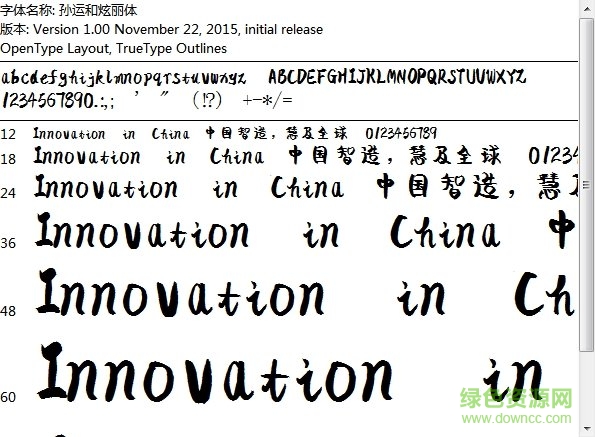
孫運(yùn)和炫麗體是一款字跡飄逸灑脫的毛筆書法字體,清爽的造型和簡約的風(fēng)韻給人張揚(yáng)而不放肆的視覺體驗(yàn),柔和的筆觸使文字變得動(dòng)靜有序起來,快來綠色資源網(wǎng)下載體驗(yàn)吧!
孫運(yùn)和炫麗體字體端正、大方,筆畫均衡粗壯,雖沒有行云流水的快感,但是也有著一股厚重的穩(wěn)重感。
孫運(yùn)和炫麗體是一款手寫風(fēng)格的書法字體,字體瀟灑大氣,整體效果非常出色,適合應(yīng)用于廣告設(shè)計(jì)、名片設(shè)計(jì)、包裝印刷、產(chǎn)品設(shè)計(jì)等應(yīng)用。